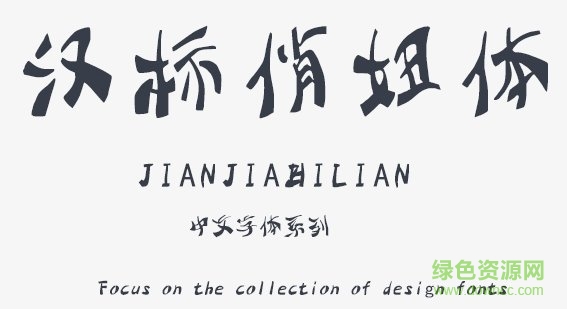
软件介绍 软件标签: 汉标俏妞体 汉标字体 可爱字体 汉标俏妞体是汉标公司全新推出的一款造型可爱、结构疏散的中文字体,每个文字均有着歪歪扭扭的造型,给人十分憨态可掬的视觉体验,更能吸引读者的注意,绿色资源网诚意推荐!汉标俏妞字体特色汉标俏妞体造型典雅而利落,结合了圆润和笔直的线条特色,给人流畅干净的造型之美,让你的海报设计、广告策划、艺术创作更显独特品味。ttf字体安装1.下载字体并解压缩;2.开始中打开控制面板;3.在控制面板中打开字体文件夹;4.把下载的字体复制到此文件夹下;5.文字添加完成绿色资源网小编点评汉标俏妞体是一款适合广告海报艺术设计的字体,字库完整,支持中英文、繁简体输入,能满足广大设计师们的日常需要。 软件截图 上一张下一张(1 / 1) 安装详细截图 其他版本下载 标题 大小 更新日期 下载 下载地址 电脑版 点击报错 软件无法下载或下载后无法使用,请点击报错,谢谢! 关闭报错反馈 请描述您所遇到的错误,我们将尽快予以修正,谢谢! *必填项,请输入内容 本类最新 dreamweaver字体库 首尔南山体字体 v1.06 官方版 潮字社风云简ttf 潮字社凌渡鲲鹏简体字体 潮字社曾玉波手书简字体 微博慧心字体 相关文章 Photoshop字体安装使用方法和技巧 如何解决“无法新增字体”问题 Win 7系统安装字体方法 网页字体大小设置方法 怎么改网页字体大小 在Linux系统中安装字体的几种方法 windows7字体显示问题:打开某些程序的时候显示的是乱码 用户评论 热门评论 最新评论 发表评论 查看所有评论(0) 昵称: 请不要评论无意义或脏话,我们所有评论会有人工审核. 字数: 0/500 (您的评论需要经过审核才能显示)